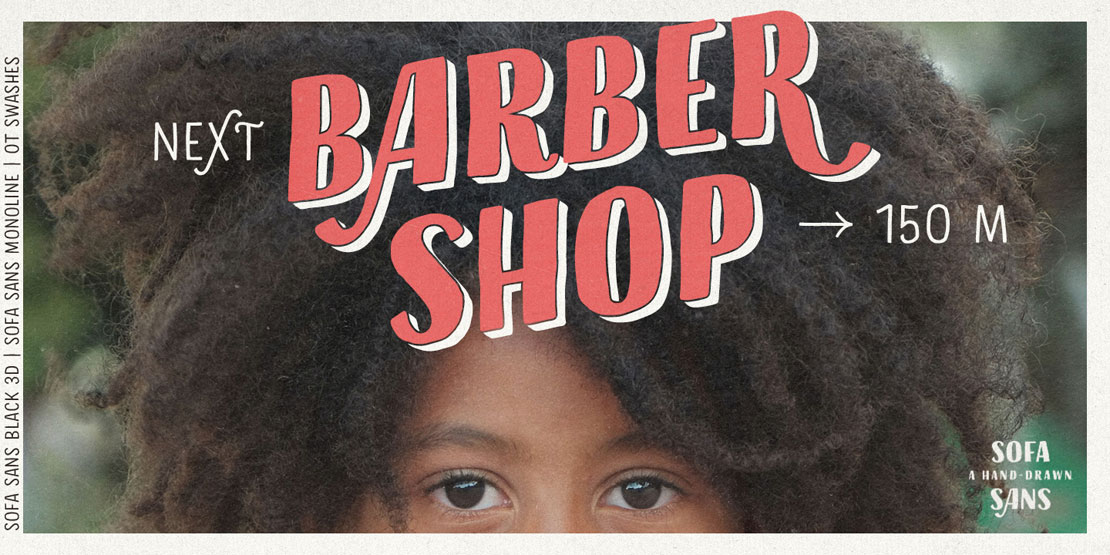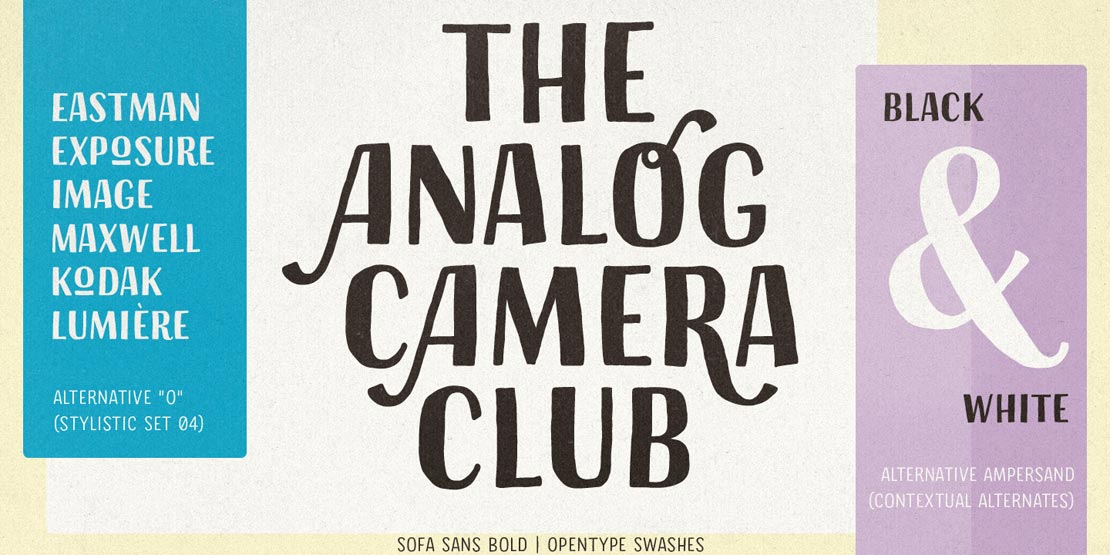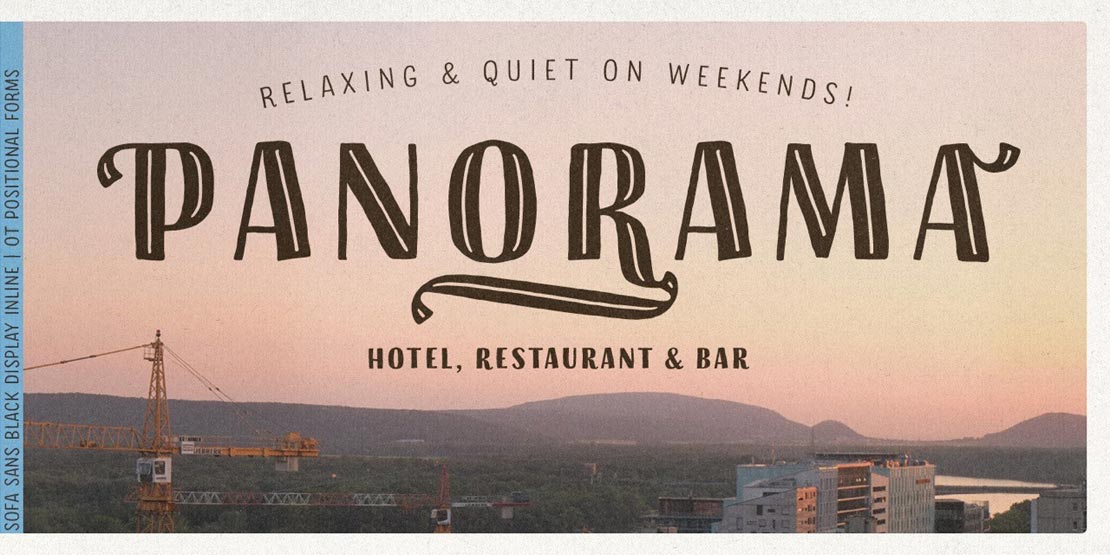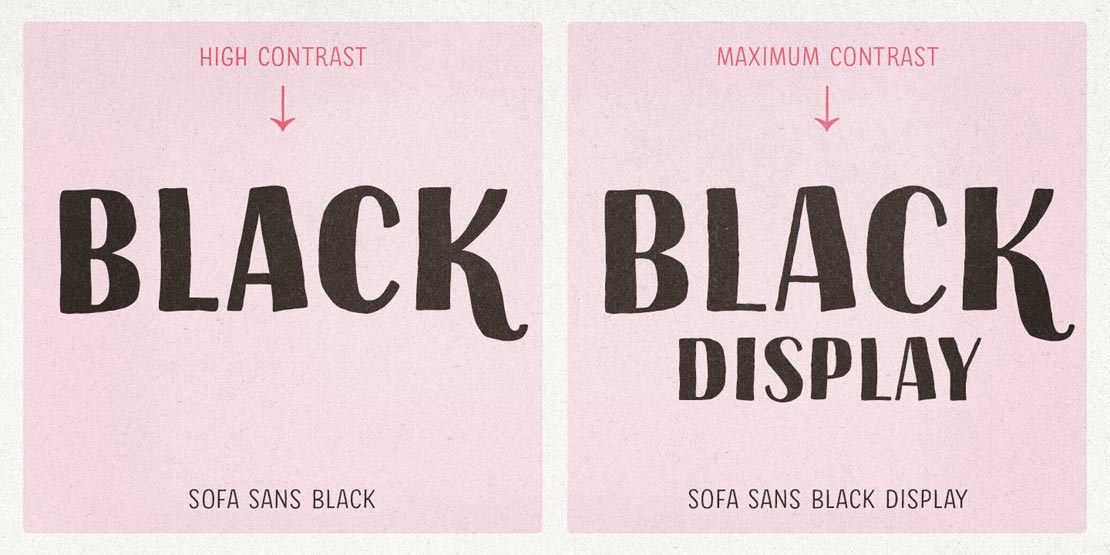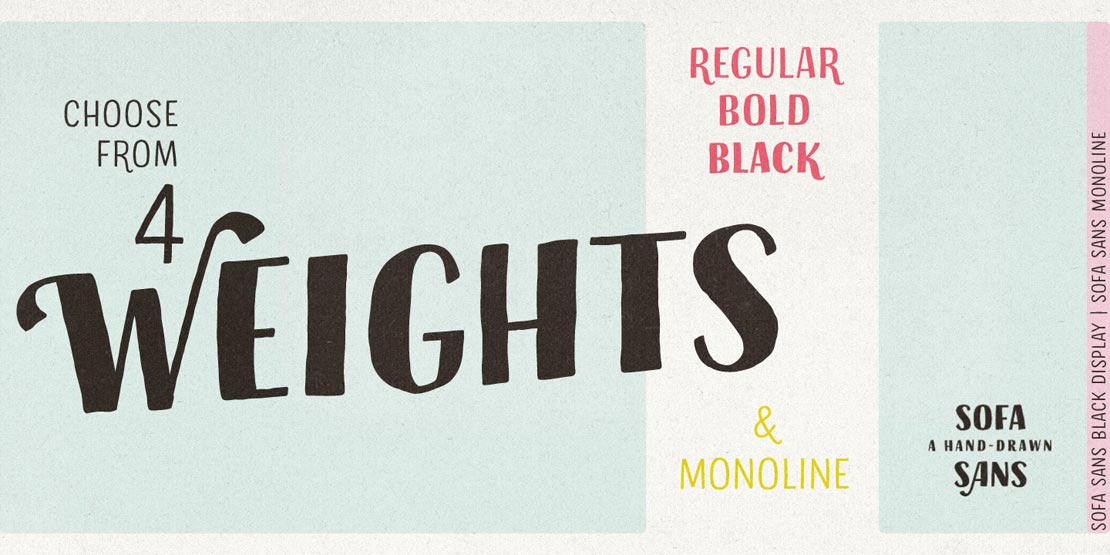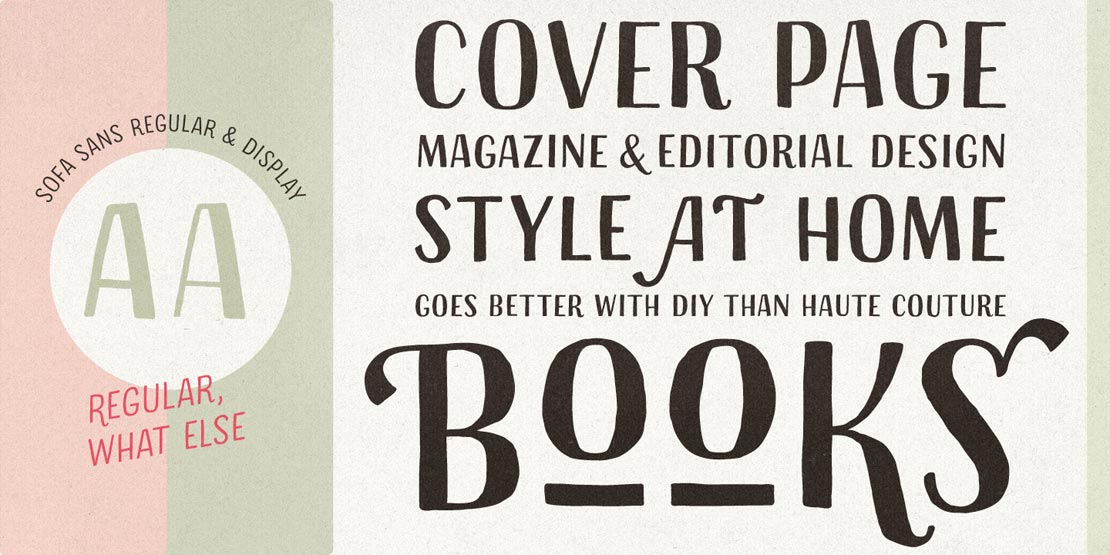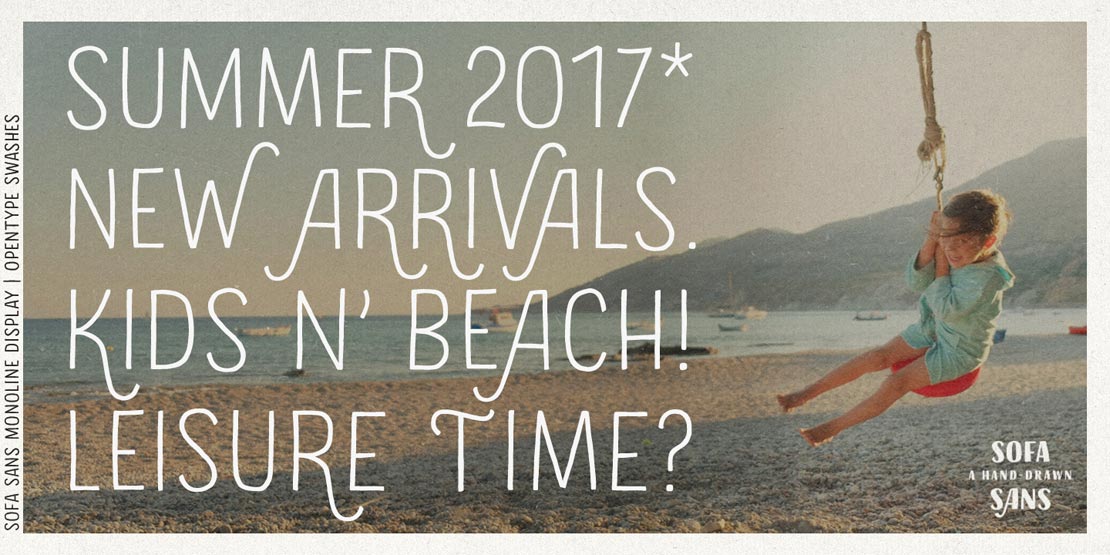
Die Sofa-Sans-Familie besteht aus 18 handgezeichneten Einzelschnitten und 4 Gewichtungen. Für Designer in Action stellt der Typedesigner 300 Gratis-Downloads der kompletten Schriftfamilie mit allen Fonts im Opentype-Format zur Verfügung!